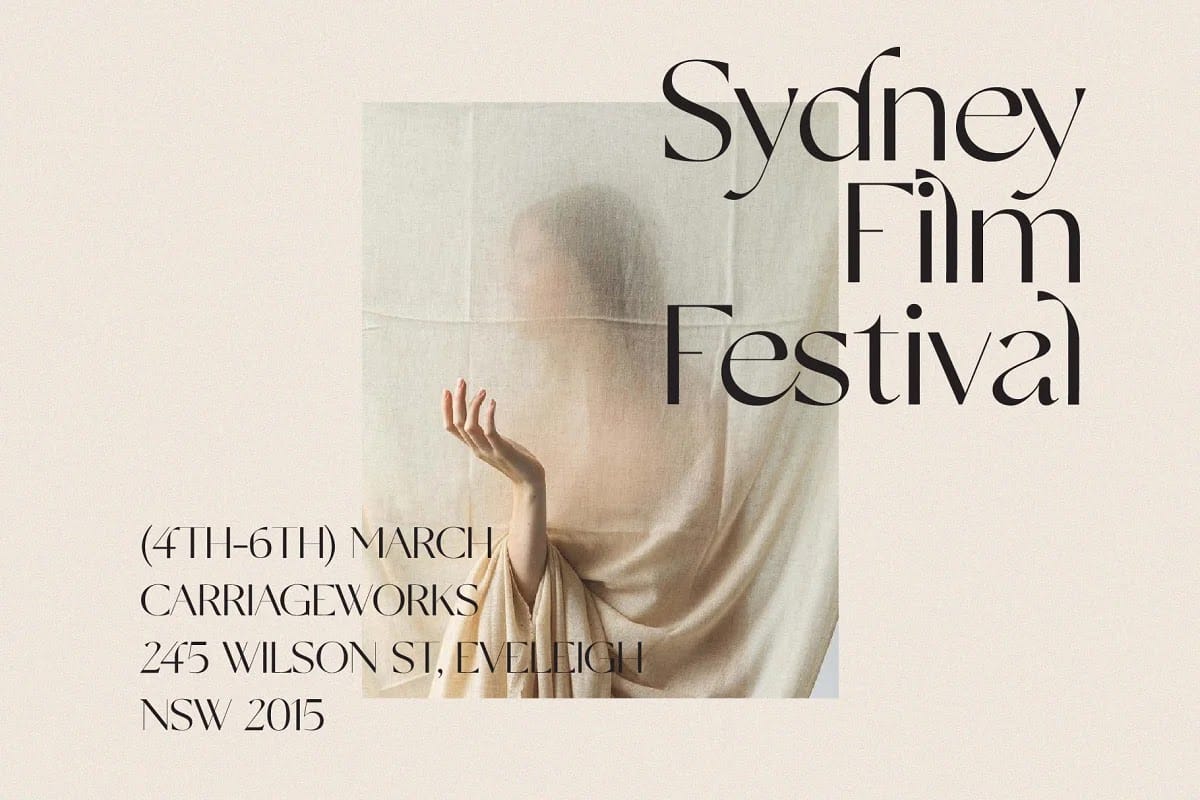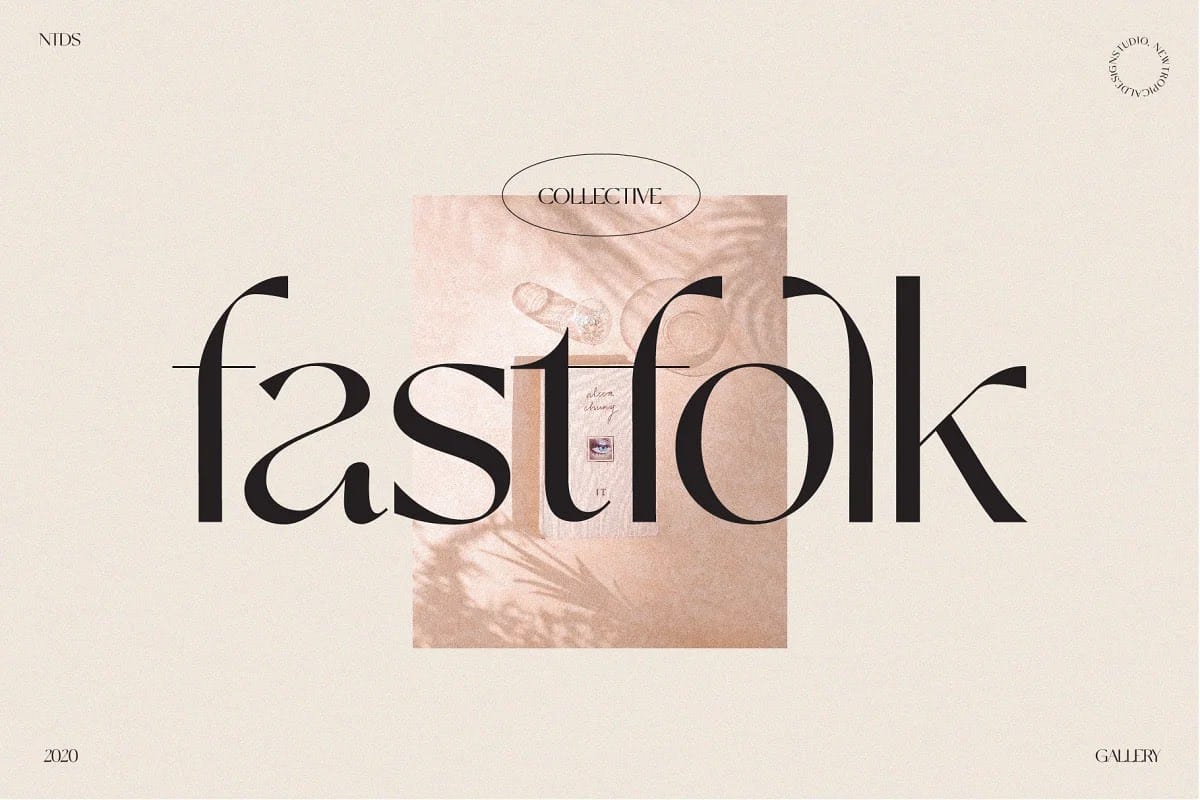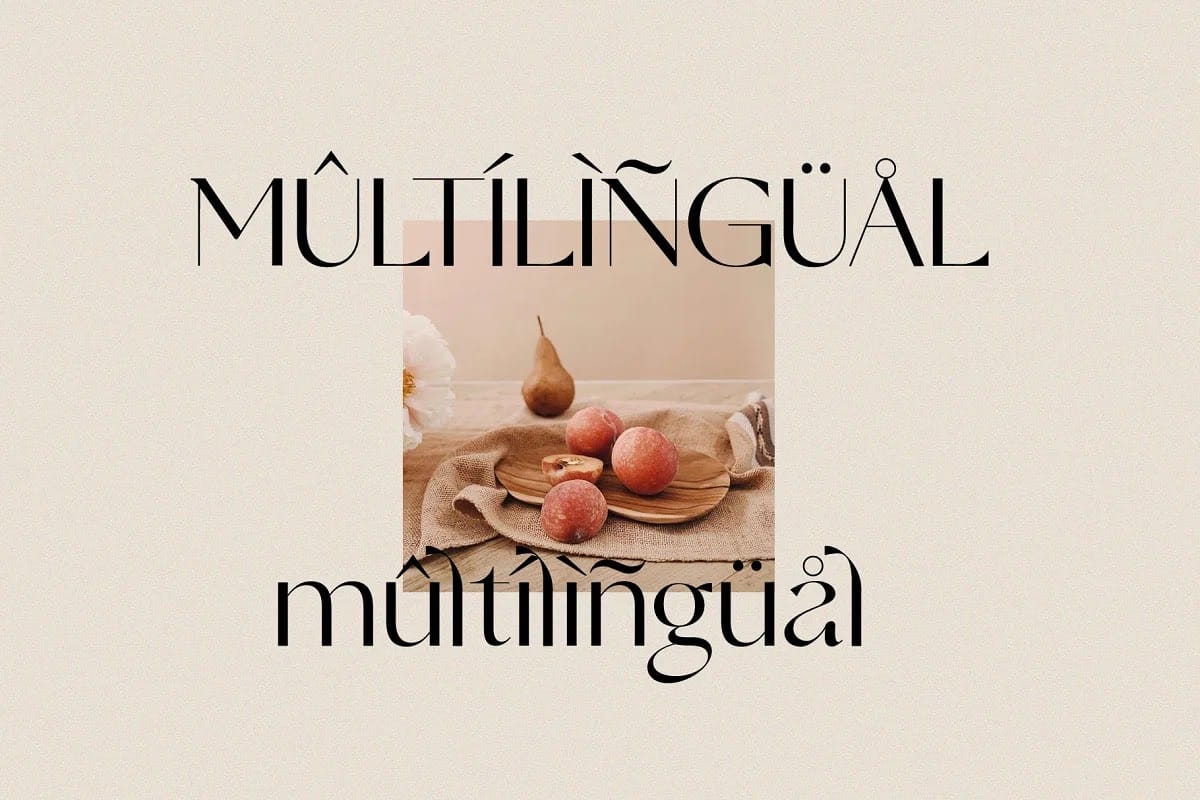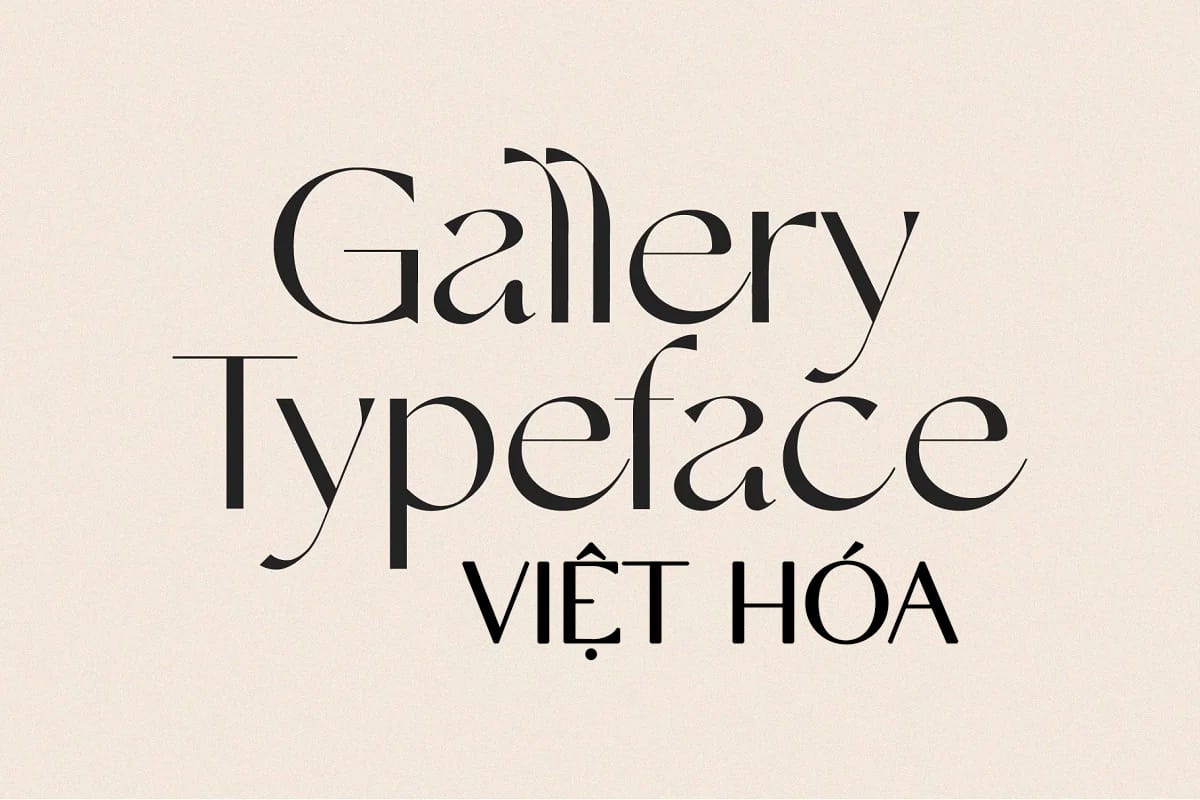
Gallery Modern Font Việt Hóa là một font chữ hiện đại. Với các thiết kế đường cong mượt mà của chữ a và thân cong của các chữ cái tăng dần tạo nên một font chữ độc đáo. Đó là sự pha trộn giữa serif cổ điển và sans serif tương lai. Thư viện có đầy đủ chữ hoa, chữ thường, số và dấu chấm câu + hỗ trợ ngôn ngữ Châu Âu. Font chữ này hoàn hảo cho thiết kế xây dựng thương hiệu hoặc biên tập liên quan đến thời trang.